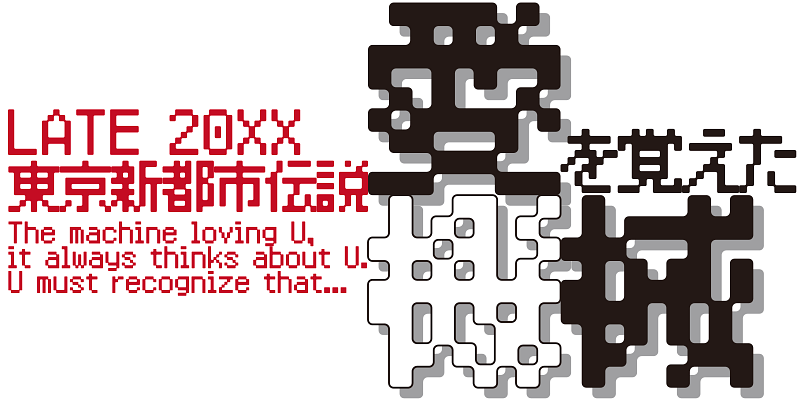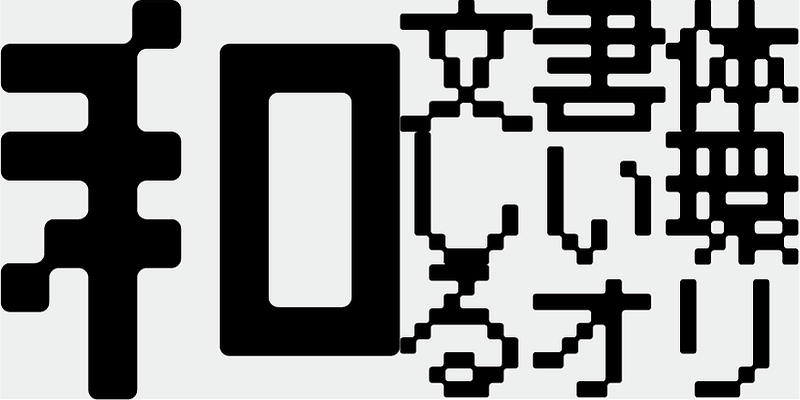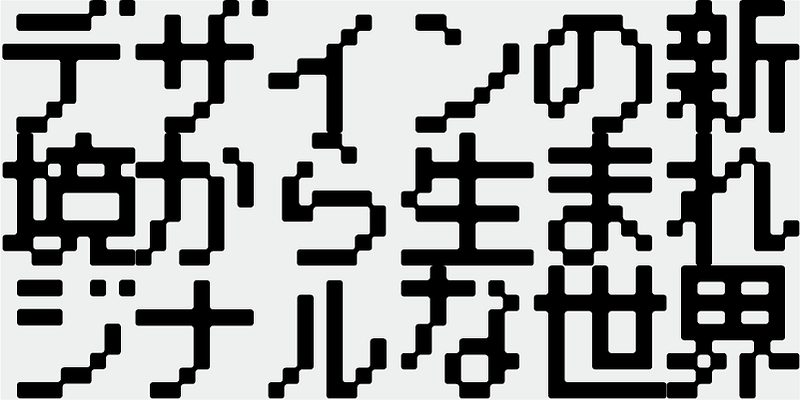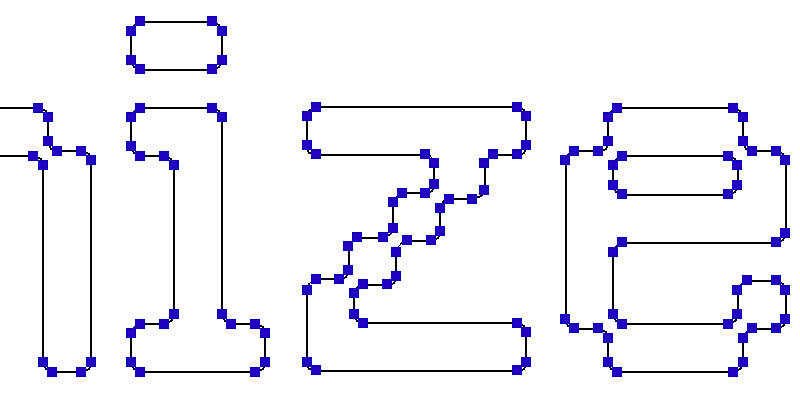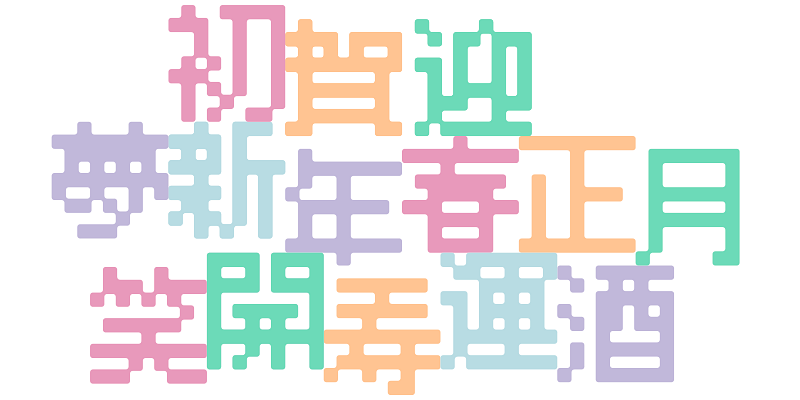
Cette police de caractères est basée sur les contours générés automatiquement à partir de bitmaps de 9 x 9 pixels. Bien que la police n’ait pas été modifiée afin d’assurer la lisibilité, elle a un aspect comique et mécanique.
Cette police comprend les 1 000 principaux caractères kanji, choisis dans les tables de fréquence des caractères établis par les sociétés de presse, les maisons d’édition et les instituts de recherche linguistique, ainsi que 206 caractères kana et signes de ponctuation.
Dans la production de polices japonaises d’aujourd’hui, les 7 000 caractères de la norme JIS sont considérés comme essentiels. Mais toutes les polices ont-elles vraiment besoin de 7 000 caractères ? À l’ère de la phototypie, on utilisait beaucoup moins de caractères. FONT1000, un groupe de typographes indépendants, a commencé par se focaliser sur cette simple question. Nous avons sélectionné le minimum de 1 000 caractères kanji (idéographiques) nécessaires pour la composition en japonais et créé activement des polices pour les prendre en charge. Ce jeu de 1 000 caractères kanji a été créé en étudiant des données de fréquence des caractères compilées par des sociétés de presse, des maisons d’édition et des organismes de recherche linguistique, etc. Il comprend également des caractères syllabiques kana et des signes de ponctuation. FONT1000 a été créée en 2001 avec 25 designers et 25 polices de caractères. Aujourd’hui, nous avons 130 polices et comptons désormais près de 40 membres, ce qui permet de travailler sur des polices avec plus de caractères.